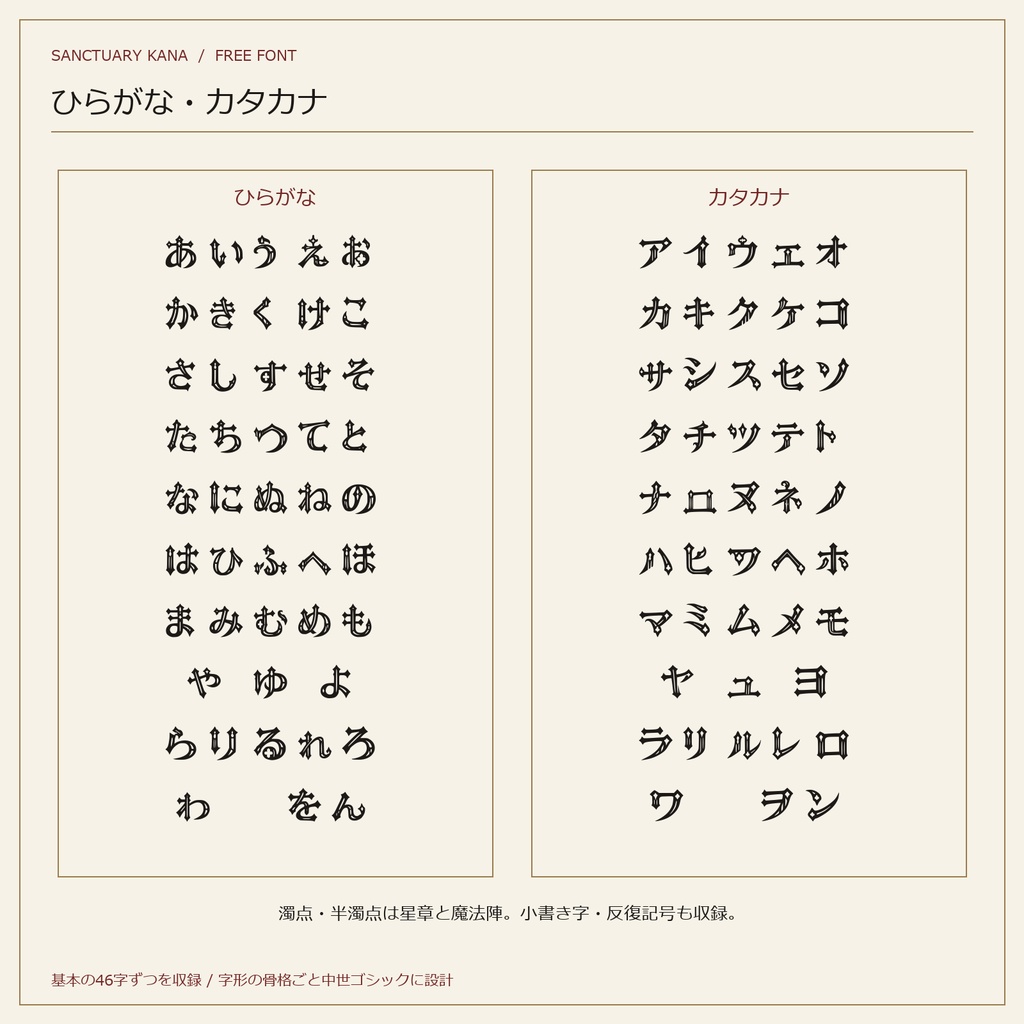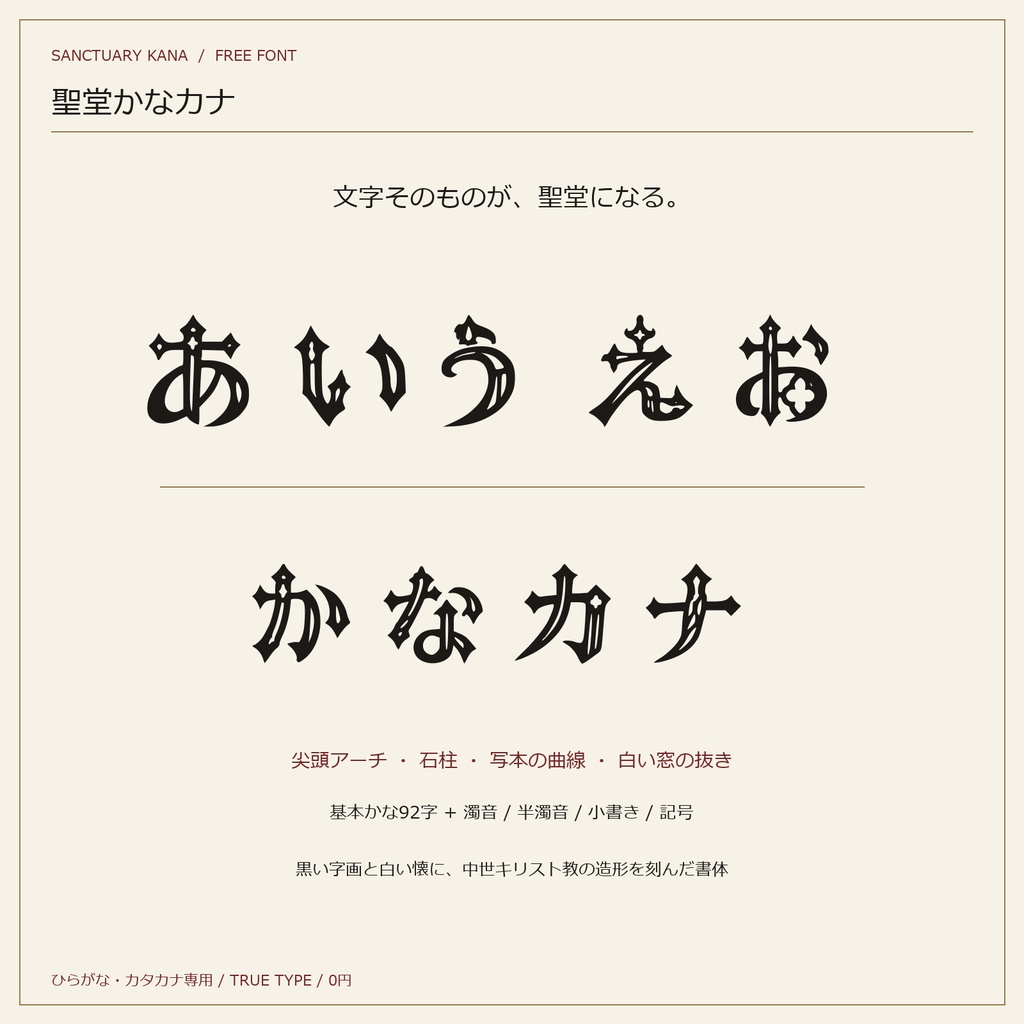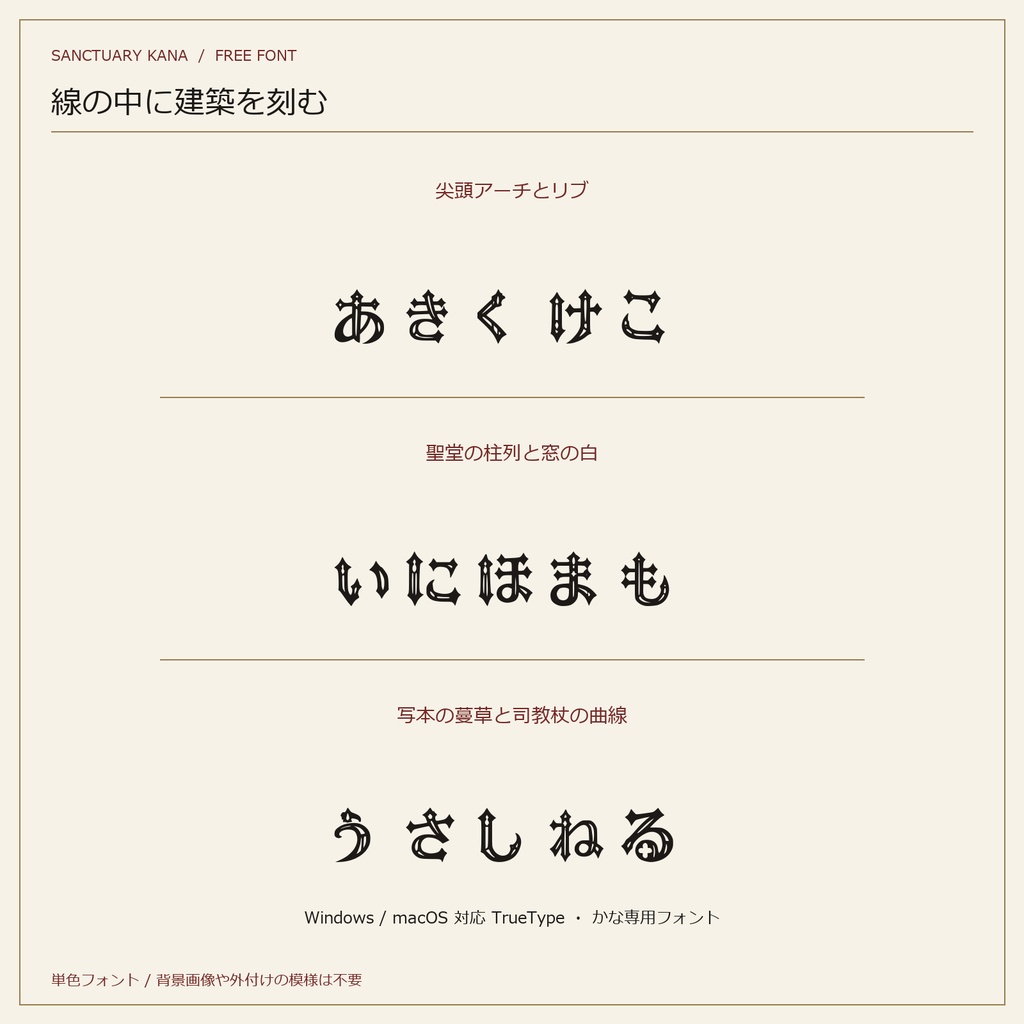
聖堂かなカナ|中世キリスト教ゴシック装飾のかなフォント【無料】
文字そのものが、聖堂になる。 尖頭アーチ、聖堂の柱、写本の蔓草、ステンドグラスの白い抜き。中世キリスト教の造形を背景に置くのではなく、かなの線と内側の空間そのものに織り込んだ白黒の装飾フォントです。 ■ 収録内容 ・ひらがな46字、カタカナ46字 ・濁音、半濁音、小書きかな、反復記号、句読点、長音、アイヌ語カタカナ拡張 ・合計196字形。漢字・ラテン文字は収録していません。 ・TTFフォント、字形一覧、見本、全字の設計指示をZIPに同梱 ■ 字形の意匠 ・尖頭アーチやリブを黒い字画にする ・字の懐をステンドグラスの白い開口として抜く ・濁点は「✢」型の四方星を二つ、半濁点は二重円と3×3方陣の魔法陣にする 一字ずつの設計指示と白黒造形の説明を同梱しています。 ■ 形式・用途 TrueType(TTF) / Windows・macOS 見出し、タイトル、表紙、ロゴ、動画、ゲーム、配信、印刷物向け。 かな専用の装飾書体です。本文用途には向きません。 ■ 利用条件 個人・商用制作物に無料で利用できます。クレジット表記は任意です。 フォントデータ自体の再配布、共有、転売、公開Webフォント配信は禁止です。詳細はZIP内のLICENSE_JA.txtをご確認ください。